今回は、「惡」「學」「體」など、旧字体・正字体が使える日本語フリーフォントをご紹介します。
古い文献や歴史的な資料、古典文学の再現や和風デザインなどでは、常用漢字とは異なる旧字・正字を使いたい場面があります。しかし、多くのフォントでは旧字体の収録が限定的だったり、正しく表示されないことも少なくありません。
そこで今回は、古典的な表現に適した明朝体など、歴史的な雰囲気をまとうデザインフォントなど、「旧字が使える」「旧字体が美しく表現できる」ことに重点を置いた日本語フリーフォントをピックアップしました。
旧字・正字で“和”を表現!伝統的な日本語フリーフォント
以下のようないつも見慣れた漢字とはちょっと違った「旧字・正字」が使えるフリーフォントをご紹介します。
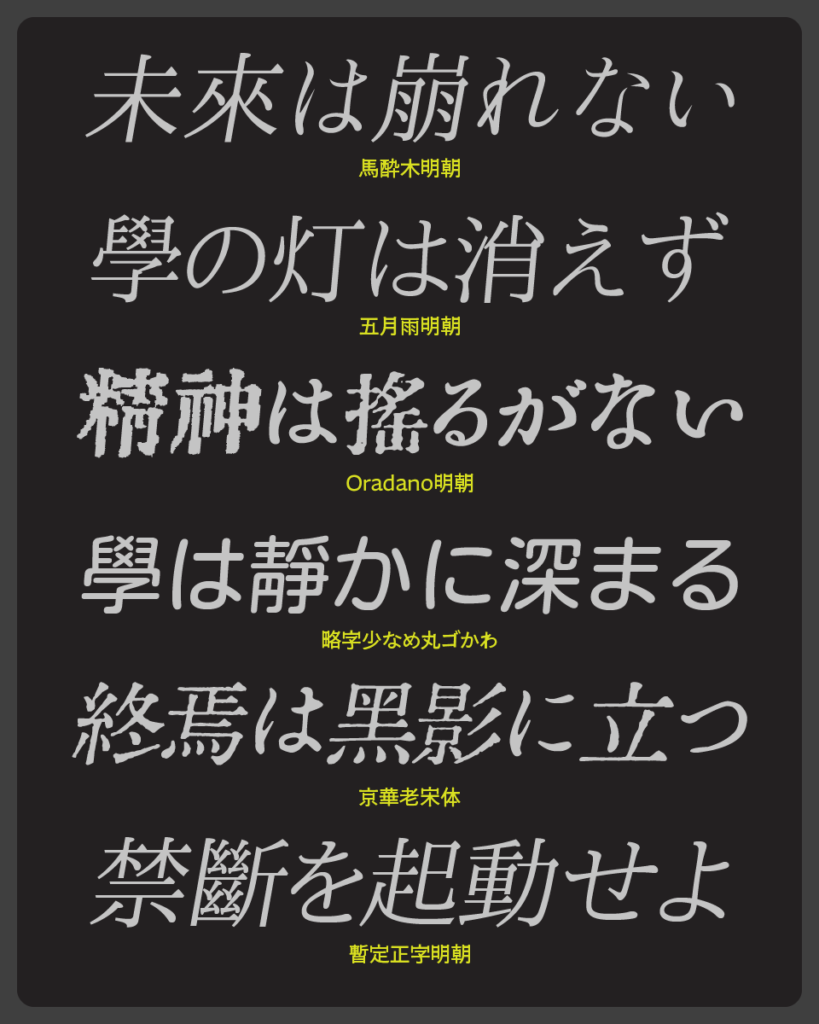
IPA明朝
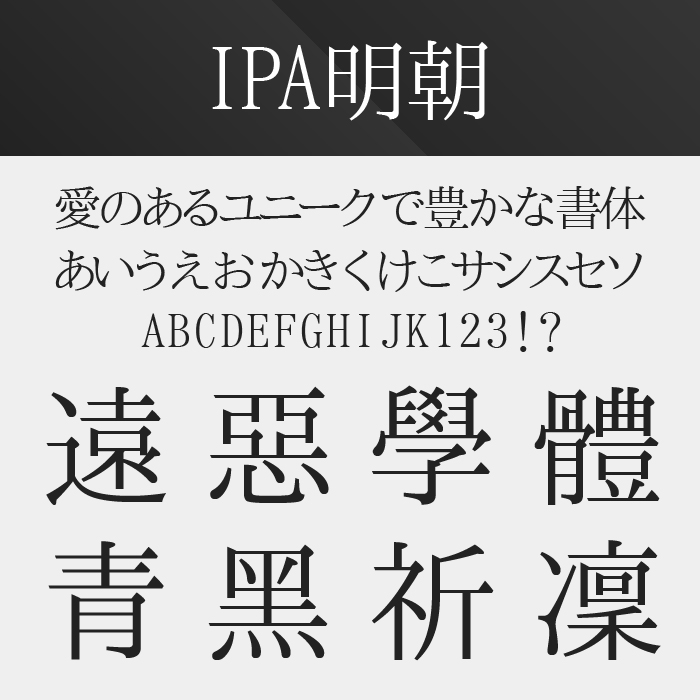
IPA明朝は、オープンライセンスで広く使用されているスタンダードな明朝体で、正字(旧字体)にも安定して対応しています。読みやすさと美しさのバランスが取れており、印刷物や文芸的な用途にぴったりなフォントです。特に横画や縦画の繊細な表現が、漢字本来の格調を引き立てています。
京華老宋体
京華老宋体フォントは、中国の古典的な宋朝スタイルをベースにした明朝体で、漢字の旧字体表現にもぴったりです。活版印刷のようなにじみを感じさせるタッチが特徴的で、文語文やレトロな雰囲気の強い作品にマッチします。
五月雨明朝
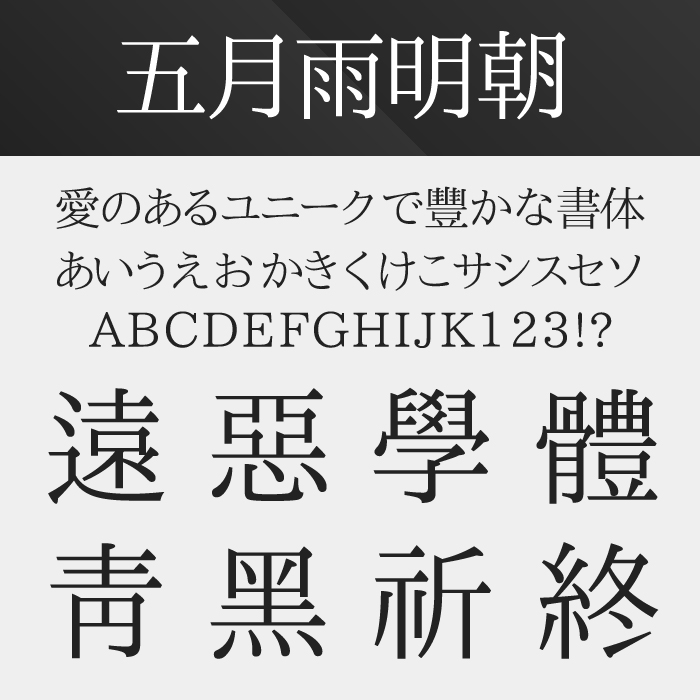
五月雨明朝は、やさしさと透明感のある現代風明朝体です。旧字体にも対応しつつ、柔らかく優美な印象を持っています。清楚で控えめな線の揺らぎがあり、詩や短歌、手紙風の表現に向いています。
馬酔木明朝(あせびみんちょう)
馬酔木明朝は、文芸・叙情的なコンテンツにぴったりのやわらかで優雅な明朝体です。旧字体や異体字の収録も豊富で、古典的な文章や詩の演出に最適です。縦画と横画に絶妙な抑揚があり、品のあるレトロ感を演出できます。
Oradano明朝
Oradano明朝は、活版印刷のような風合いが特徴的な明朝体で、旧字も対応。印刷のかすれや劣化を模したテクスチャが施されており、まるで古書や新聞のような雰囲気を持っています。
XANO明朝
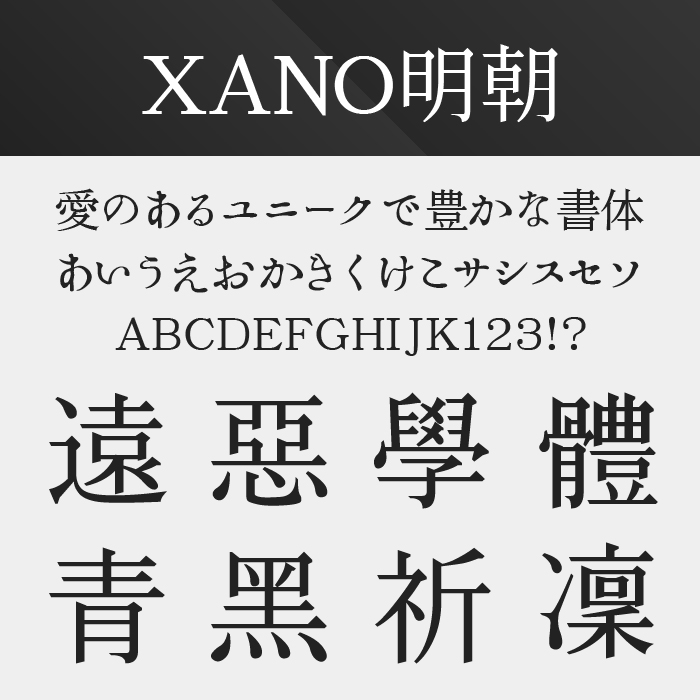
XANO明朝は、力強さと品格を併せ持つ明朝体で、旧字にも丁寧に対応しています。特に見出しでの存在感が際立ち、活字風のクラシカルな趣が漂います。モダンさも残しつつ、文語的・文学的な表現にも違和感なくマッチします。
大正活字っぽいフォント
大正活字っぽいフォントは、活字印刷の滲みやズレを忠実に再現し、昭和初期〜大正時代の印刷物のような雰囲気を感じさせてくれるフォントです。